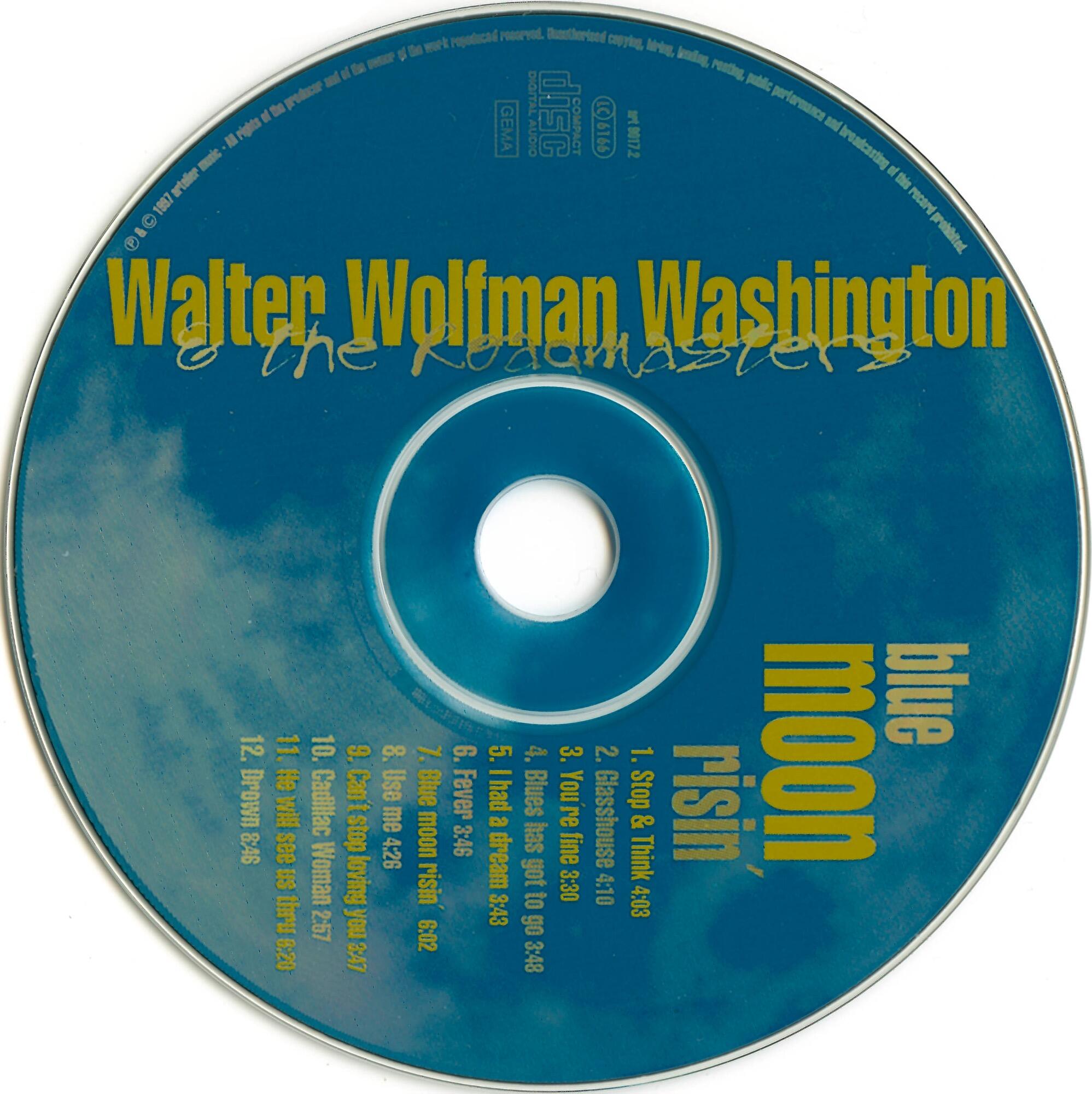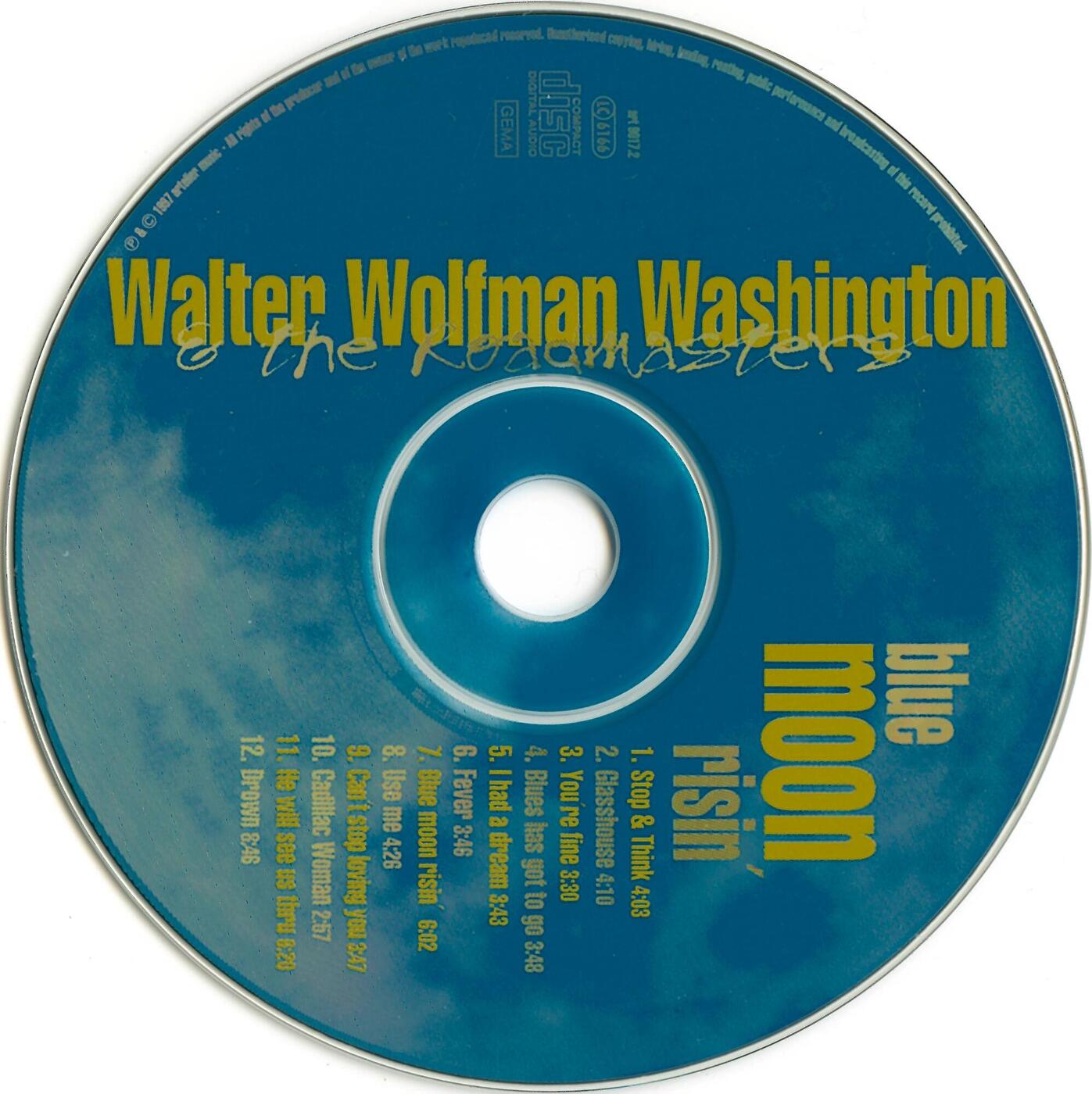
Fette schmallaufende Schrift auf CD Blue Moon Risin
Ich habe hier ein CD-Cover von 1987, für das ich für den Rechteinhaber neue Daten erstellen soll. Die Originaldaten sind nicht mehr aufzufinden, wahrscheinlich laufen die auch nicht mehr mit heutiger Software. Ich dachte, die Schrift sei die IMPACT, aber als ich sie dann drüber gesetzt habe, stellte ich fest, dass die doch deutlich anders ist, zum Beispiel der Abstrich vom kleinen „r“ geht viel tiefer.
Erkennt jemand von Euch die Schrift?